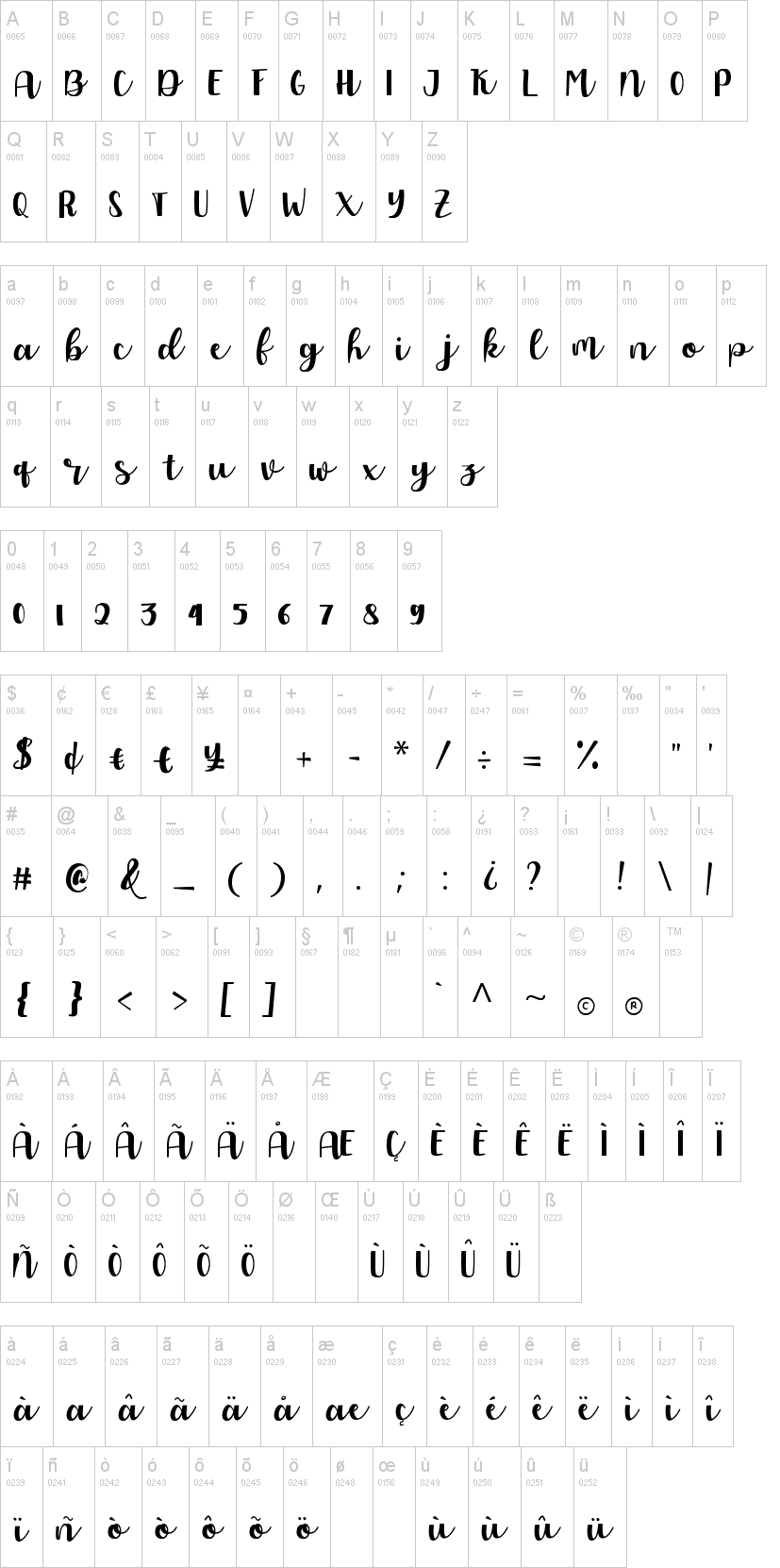
Allyca
Allyca 字体是一款现代技术感觉的混合字体,适用于任何场景。它结合了硬朗的结构和优雅的曲线,形成了一种统一的外观,可以用于品牌标识、广告、海报、标题、标签等。它的特点是清晰的细节、简洁的线条、宽松的字体空间以及更多变化的字形,可以满足不同的设计需求。
Allyca是一款非常不错的手写艺术字体,具有很好的视觉感,适合于文化类的宣传设计、商业类品牌的广告和产品包装设计以及个性化文字排版等较多场景。
Allyca字符映射图